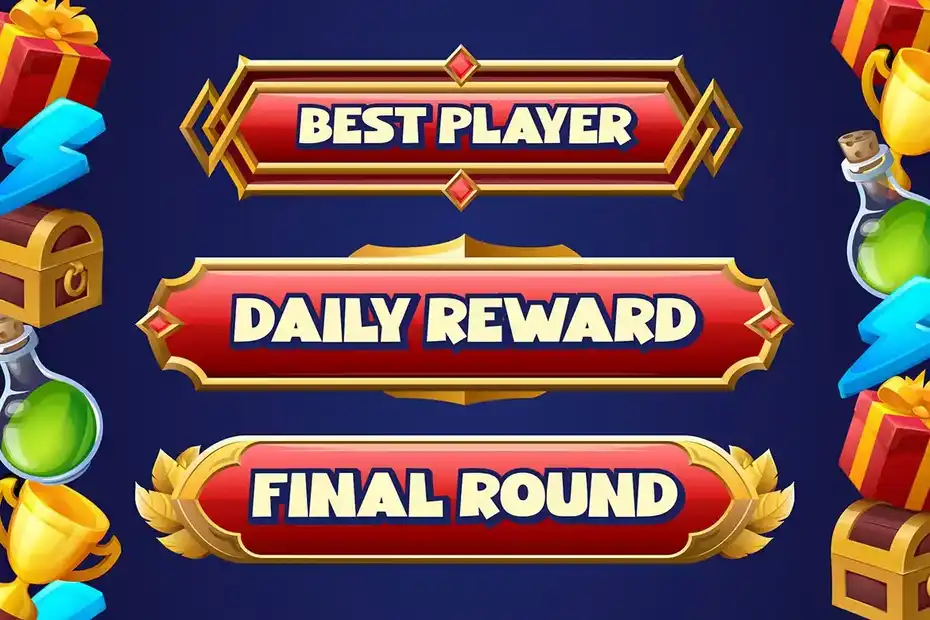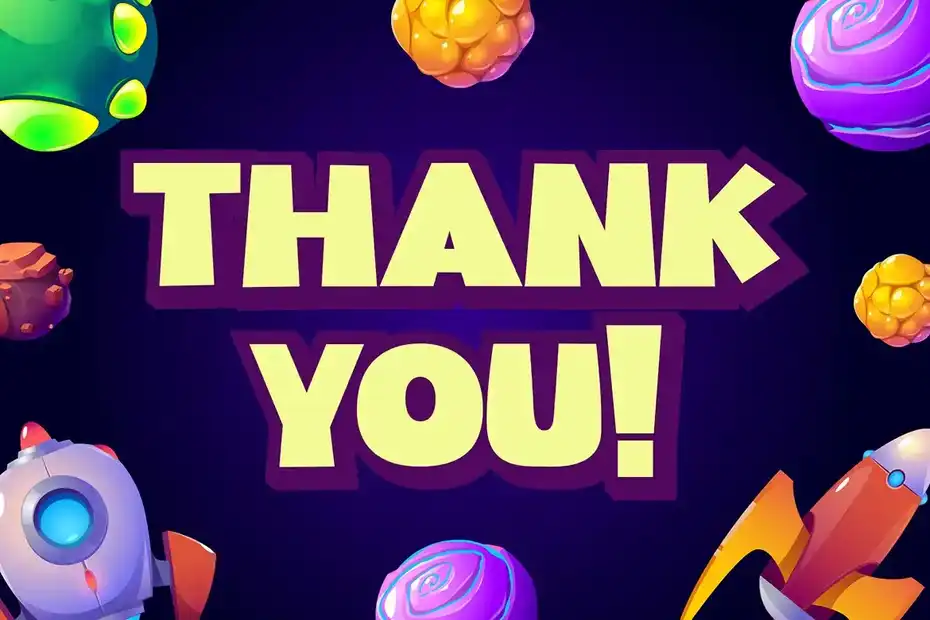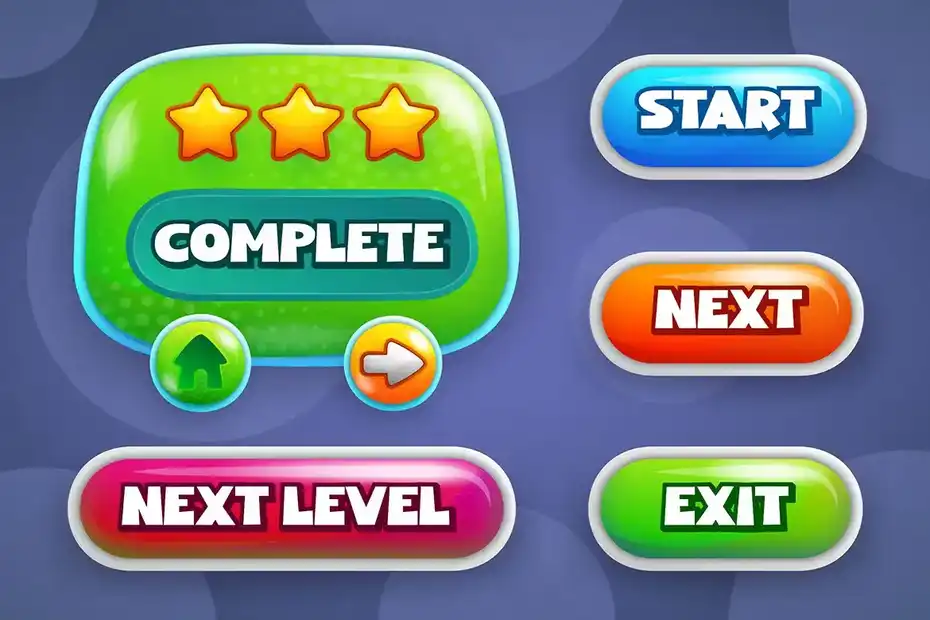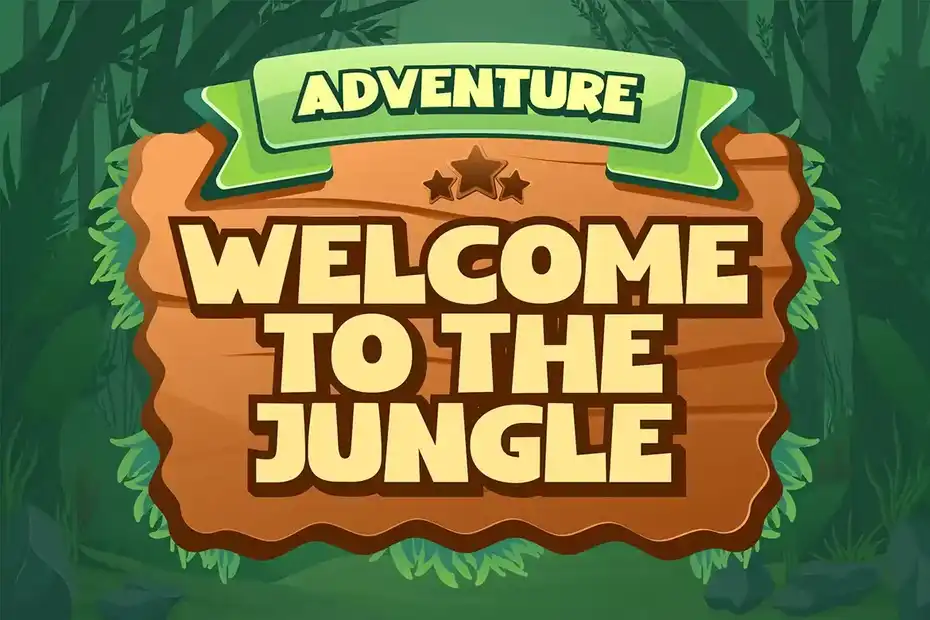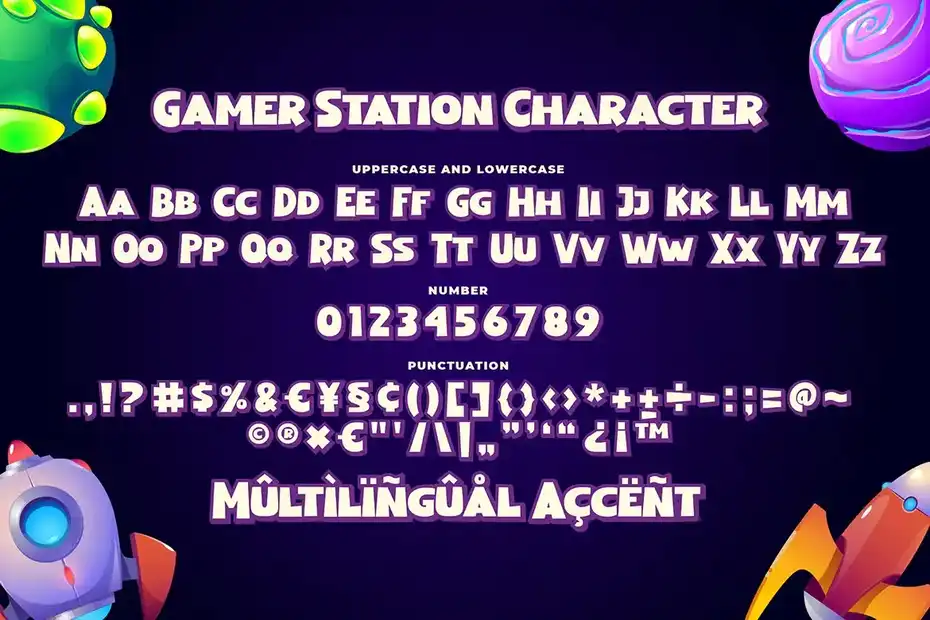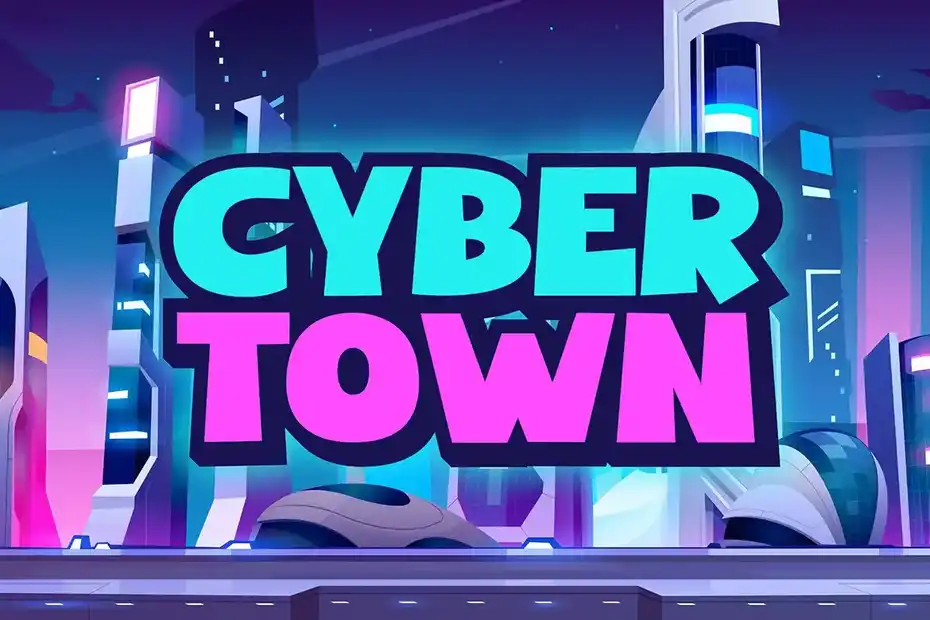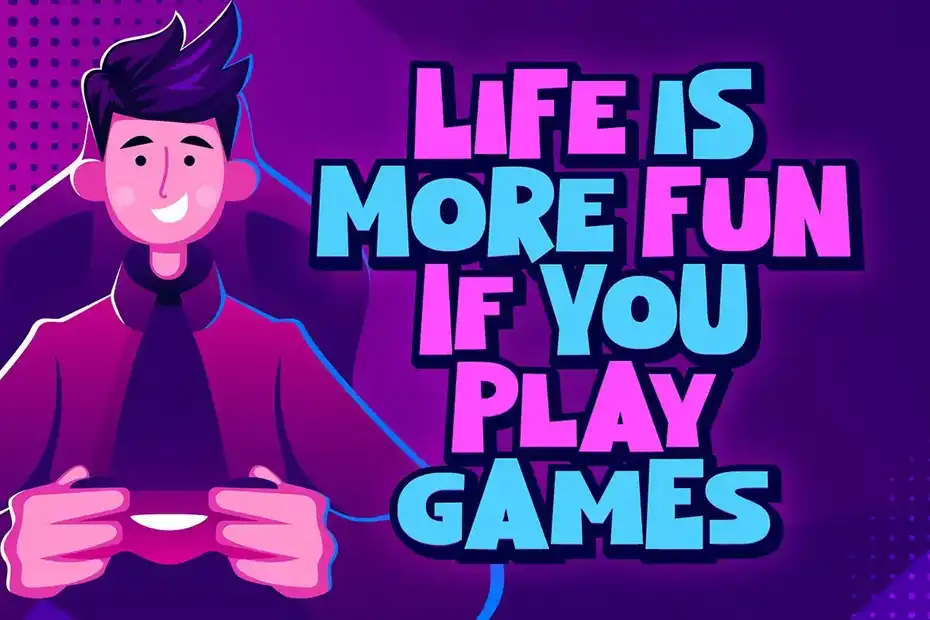
دانلود فونت گیمر استیشن، یک فونت بازی جذاب Gamer Station a Playful Game Font : این مجموعه شامل یک فونت انگلیسی فانتزی است که برای بازی، جلد کتاب، کتاب کودکان، کمیک، پوستر، بسته بندی، کالا، لوگو و غیره مناسب میباشد.